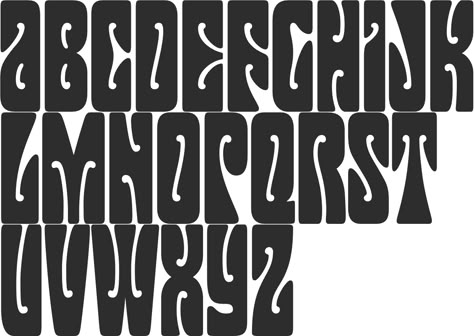
Психология восприятия шрифтов. Как ее применять?
Есть ряд различных элементов, которые вы можете использовать в своих рекламных и дизайнерских проектах, чтобы вызвать определенные эмоции. Цвета, формы, дизайн создают широкий спектр чувств у вашей аудитории — от счастья до грусти и волнения. Но есть один элемент, который часто упускают из виду, а он может оказать огромное влияние на эмоциональную реакцию — и это шрифт.
Психология восприятия шрифта — мощная вещь. Шрифты, которые вы выбираете для своих дизайнов, могут кардинально изменить то, как этот дизайн воспринимается аудиторией и какие эмоции он вызывает.
Но что такое психология восприятия шрифтов? Почему она так важна? И как вы можете использовать ее для формирования эмоций?
Что такое психология восприятия шрифтов?
Прежде чем мы перейдем к тому, почему психология восприятия шрифтов так важна (и как использовать ее, чтобы вдохновить аудиторию на конкретные эмоциональные реакции), давайте поговорим о том, что именно она собой представляет.
Если коротко, психология шрифтов — изучение того, как разные шрифты влияют на мысли, чувства и поведение.
У людей очень разные (и часто очень специфические) мысли, чувства и ассоциации с разными типами шрифтов. Например, когда вы используете Comic Sans в дизайне, это создаст совершенно иной эмоциональный отклик для вашей аудитории, чем если бы вы использовали Arial, Roboto или Montserrat. А когда вы выбираете Times New Roman в качестве основного шрифта, люди будут ассоциировать его с совершенно другими мыслями, чувствами и идеями, чем если бы вы выбрали Yellowtail или Baloo. Понимание этих ассоциаций и эмоциональных реакций и того, как использовать их в своих интересах, и составляет психологию восприятия шрифтов.
Понимание психологии восприятия шрифта является обязательным условием, если вы хотите получить эффектный дизайн.
Почему психология восприятия шрифтов так важна?
Одна из самых веских причин, по которой вам следует использовать психологию восприятия шрифтов, — она позволяет вам выбрать правильные шрифты для ваших проектов и дает вам массу контроля над тем, как ваш дизайн воспринимается и принимается вашей целевой аудиторией.
Допустим, вы разрабатываете рекламу новой линии детской одежды и хотите, чтобы аудитория чувствовала себя счастливо, когда видела эту рекламу. Выбор более причудливого шрифта создаст эмоциональный отклик, который вы ищете, в то время как традиционный шрифт, скорее всего, с задачей не справится.
Дело в том, что, когда вы создаете дизайн, вы ищете очень специфическую реакцию вашей аудитории. А когда вы понимаете психологию восприятия шрифтов, вы контролируете ту самую эмоциональную реакцию.
Если вы хотите, чтобы дизайн соответствовал предпочтениям вашей аудитории, важен выбор правильных шрифтов. Избегайте нецелесообразного использования шрифтов.
Выбор неправильного шрифта может полностью изменить внешний вид вашего дизайна и, как следствие, изменить реакцию вашей аудитории. Предположим, что вы создаете обложку на Facebook, чтобы рекламировать новую финансовую консалтинговую компанию. В более традиционной индустрии, такой как финансы, вы хотите вызвать у аудитории чувство доверия и стабильности, но выбор неправильного шрифта сделает ваш дизайн слишком непринужденным.
Итог: некорректный выбор шрифтов может отрицательно повлиять на ваш дизайн. Понимание психологии восприятия шрифтов так важно, потому что это помогает вам избежать тех самых, неидеальных шрифтов.
Психология шрифта влияет на результат
Какова же последняя причина того, почему психология восприятия шрифтов так важна? Потому что она действительно работает.
У каждого дизайна есть цель. И выбор шрифтов, которые будут вызывать правильный эмоциональный отклик у вашей аудитории, даст вам возможность достичь этой цели.
Например, вы разрабатываете пост в Facebook для продвижения какого-то продукта или услуги. Если вы выбираете шрифты, которые вызывают чувство восторга, эта публикация в социальных сетях заставит людей достать свои кошельки и начать покупать.
Или, может быть, вы хотите использовать Instagram, чтобы создать шум вокруг нового продукта. Использование жирного шрифта не только поможет вам выделиться в новостной ленте, но и создаст чувство предвкушения, вдохновит людей на то, чтобы заполучить ваш продукт.
Какова бы ни была ваша конечная цель, понимание того, как влияют шрифты на вашу аудиторию, поможет вам достичь этой цели.
Психология основных категорий шрифтов
Давайте рассмотрим психологию каждой из основных категорий шрифтов.
Шрифты с засечками
Шрифты с засечками – это классика. Когда вы используете их в своих проектах, ваша аудитория понимает, что вы — традиционная компания, которой они могут доверять.
Вот некоторые из ассоциаций и эмоциональных реакций, которые вы можете ожидать от использования шрифта с засечками:
-
Доверие
-
Уважение
-
Власть
-
Формальность
Шрифты с засечками отлично подходят для традиционных брендов и отраслей, включая: